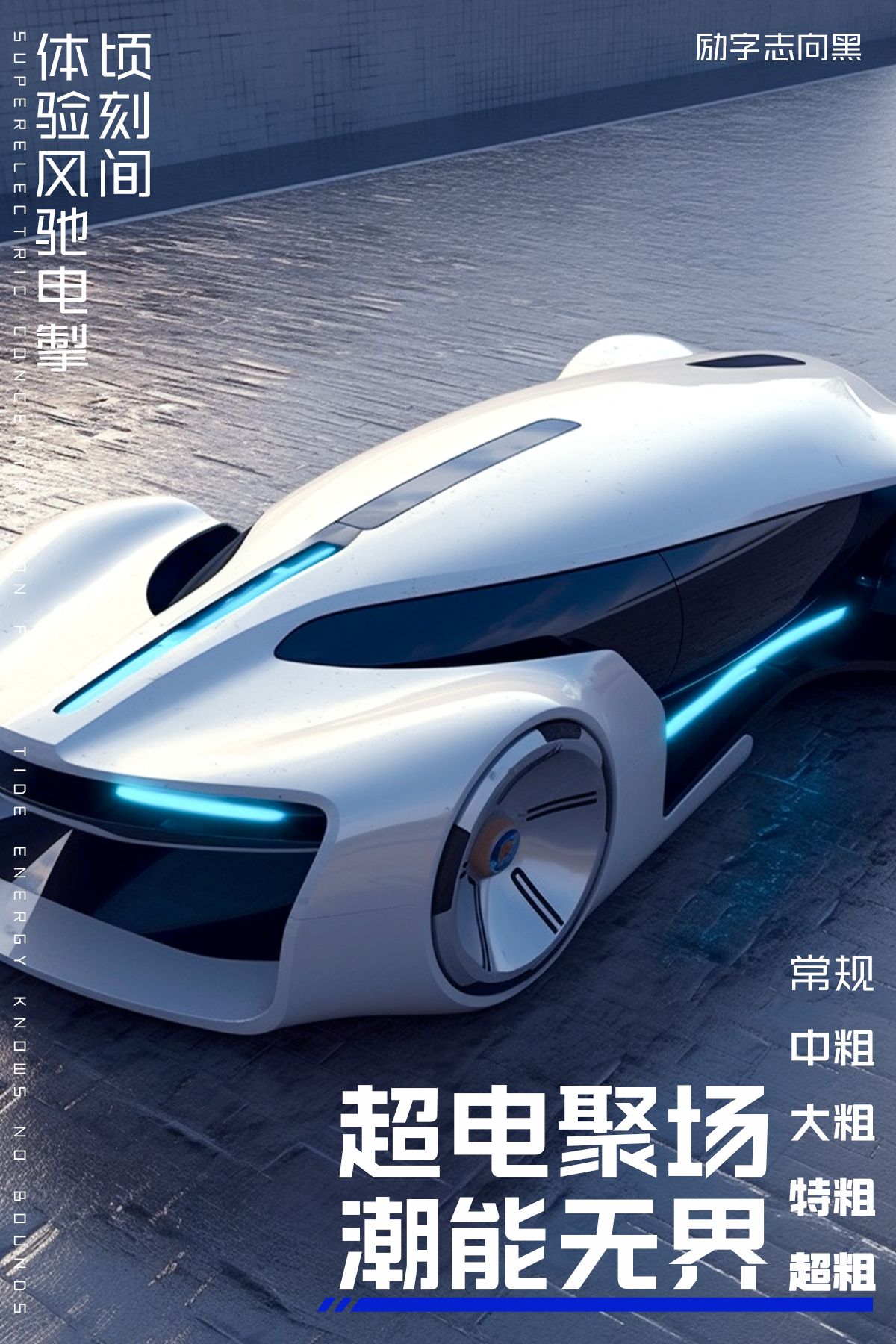
励字造梦字库是为年轻人定制的新生态字库品牌,将奇妙的灵感交锋、夸张的个性表达,融合在一笔一划中,让人人都可以成为造字侠,让更多热爱汉字设计的人,实现造字梦想。整理了2款极具青年朝气与青春感的字体,适用于五四节日海报、包装、宣传等多种场景。
励字志向黑简,以粗细均匀的直线笔画诠释青年的纯真与正直,笔画起止端平切、直切的设计,更契合青年的脾气秉性,折笔处采用外圆角设计,彰显青年人的蓬勃朝气与热血。
励字超级勇士起笔处倾斜和平直设计灵活处理,青年人的活泼灵动跃然纸上;折角笔画由外圆角与方角有序组合,撇捺弧度饱满,流畅度、舒适感满分。